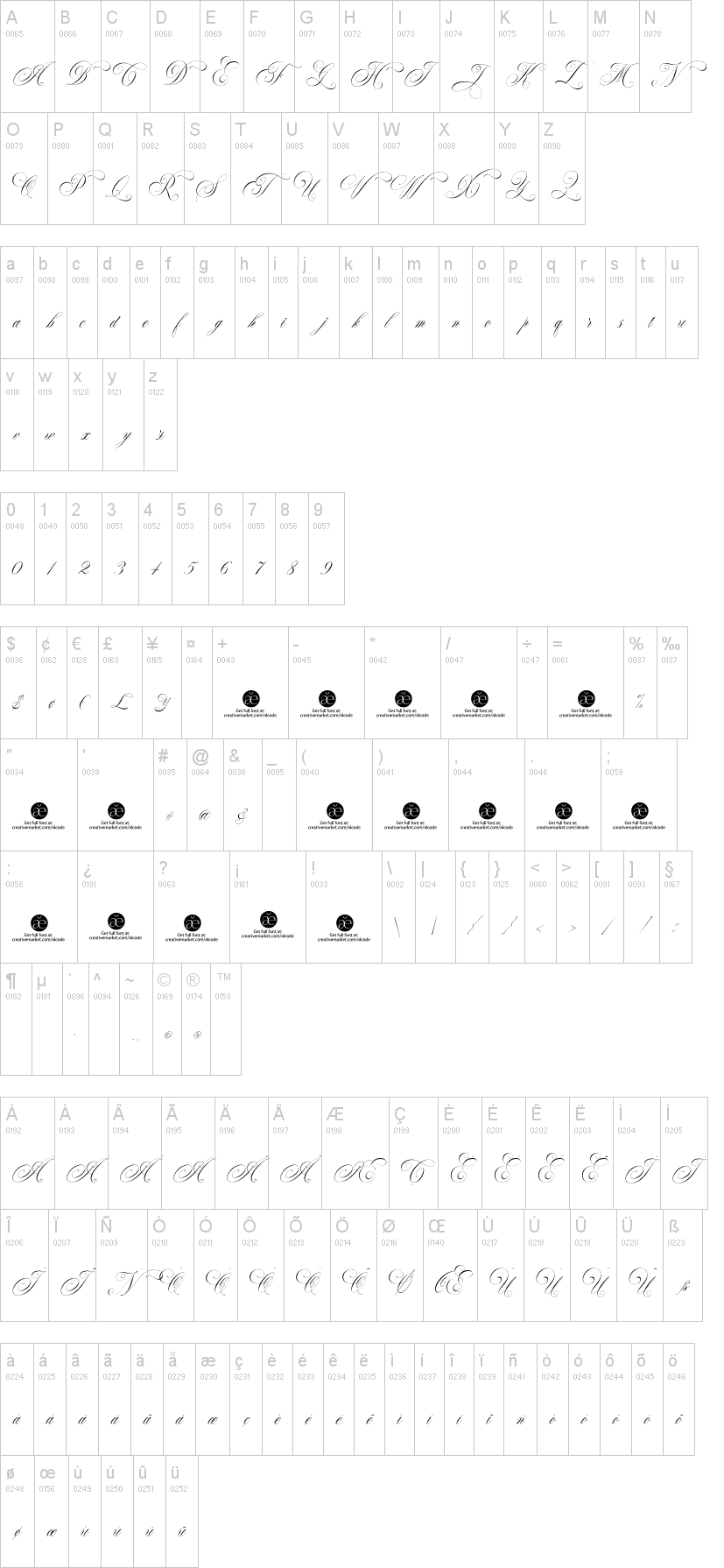
The Duality
The Duality 是一种流行的字体,它是一种手写风格的字体,可以用于各种设计项目中,例如品牌标志、海报、印刷品、网站设计等。 此字体的特点是,它融合了现代和传统的元素,展现出了一种独特的双重性感觉。每个字母都有两种不同的形式,一种是线性的,另一种是连续的,这种设计使得字体看起来很有生命力。此外, The Duality 字体的笔画有很强的对比度,线条清晰,非常适合在大字号或者较小字号的情况下使用。 总的来说,The Duality 字体的双重性感觉,清晰的线条和设计感,使得它成为了设计师们喜爱的字体之一。
The Duality是一款非常不错的手写艺术字体,具有很好的视觉感,适合于文化类的宣传设计、商业类品牌的广告和产品包装设计以及个性化文字排版等较多场景。